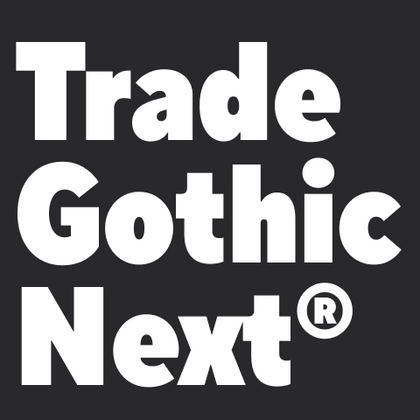
Шрифты похожие на Trade Gothic Next®
Для проектов, требующих чистых и функциональных гротесков, в коллекции TypeType представлены профессиональные решения. Если вам нужна современная альтернатива, похожая на шрифт Trade Gothic Next®, обратите внимание на наши разработки. Схожие гарнитуры сохраняют его лучшие качества и идеально подходят для корпоративных стилей и брендинга, веб-дизайна и мобильных приложений, деловой полиграфии или информационного дизайна.
Если вы устали от «заезженных» шрифтов и ищете гарнитуры, похожие на Trade Gothic Next®, ознакомьтесь с нашими лучшими альтернативами Trade Gothic Next®. Это шрифты, которые имеют близкие характеристики, но в то же время обладают новыми уникальными особенностями дизайна. Например, относятся к той же категории шрифтов, подходят для тех же целей и имеют похожие черты, но отличаются в деталях или пропорциях.
Найдите отличную замену Trade Gothic Next® и попытайтесь имитировать похожее настроение, передать нужное вам ощущение, используя его в своих проектах. Каждый шрифт, представленный на этой странице, является двойником шрифта Trade Gothic Next®, фактически его полным аналогом.
TT Commons™ Classic является универсальным гротеском с минимальным контрастом штрихов, закрытой апертурой и геометрическими формами знаков. Дизайн гарнитуры разрабатывался для максимально широкого круга задач, с которыми обязан справляться любой качественный корпоративный шрифт.
TT Interphases Pro — неогротеск, который создавался специально для работы в интерфейсах. Среди визуальных особенностей TT Interphases Pro — плавные формы скруглений, повторяющиеся во всех элементах: благодаря им большие массивы текста читаются легко и приятно.
TT Chocolates — изящный гуманистический гротеск сo сбалансированными пропорциями, близкими к классическим. Шрифт с приятным дружелюбным характером, который интуитивно воспринимается как что-то знакомое.
TT Norms Std Condensed является логическим развитием нашего бестселлера TT Norms Pro. Несмотря на то, что шрифт обладает более узкими пропорциями относительно исходной гарнитуры, он унаследовал классические пропорции знаков, внимание к деталям и дотошную проработку каждого знака в шрифте.
TT Backwards Sans — это узкий гротеск, пластичностью своих знаков отсылающий нас в книжное оформление конца 70-х — начала 80-х годов и выполненный с учетом использования в маленьком размере текста. Магазинные вывески, постеры и плакаты, книжное оформление — вот где мы черпали вдохновение для нашего проекта.
TT Berlinerins — это контрастная пара шрифтов, которая по сути является нашим трибьютом Берлину. Также, как и в самом городе переплетаются историчность и современность, так и в нашем шрифтовом семействе элегантный скрипт символизирует собой современный Берлин, а гротеск, выполненный в стиле плакатных wood-type шрифтов первой трети 20-го века, отвечает за историческую составляющую города.
TT Corals — это современный гуманистический гротеск, который имеет очень много характерных исторических черт начала 20-го века. Шрифт хорошо подойдет для темы классической литературы или музыки, а также для других самых разнообразных творческих областей человечества.